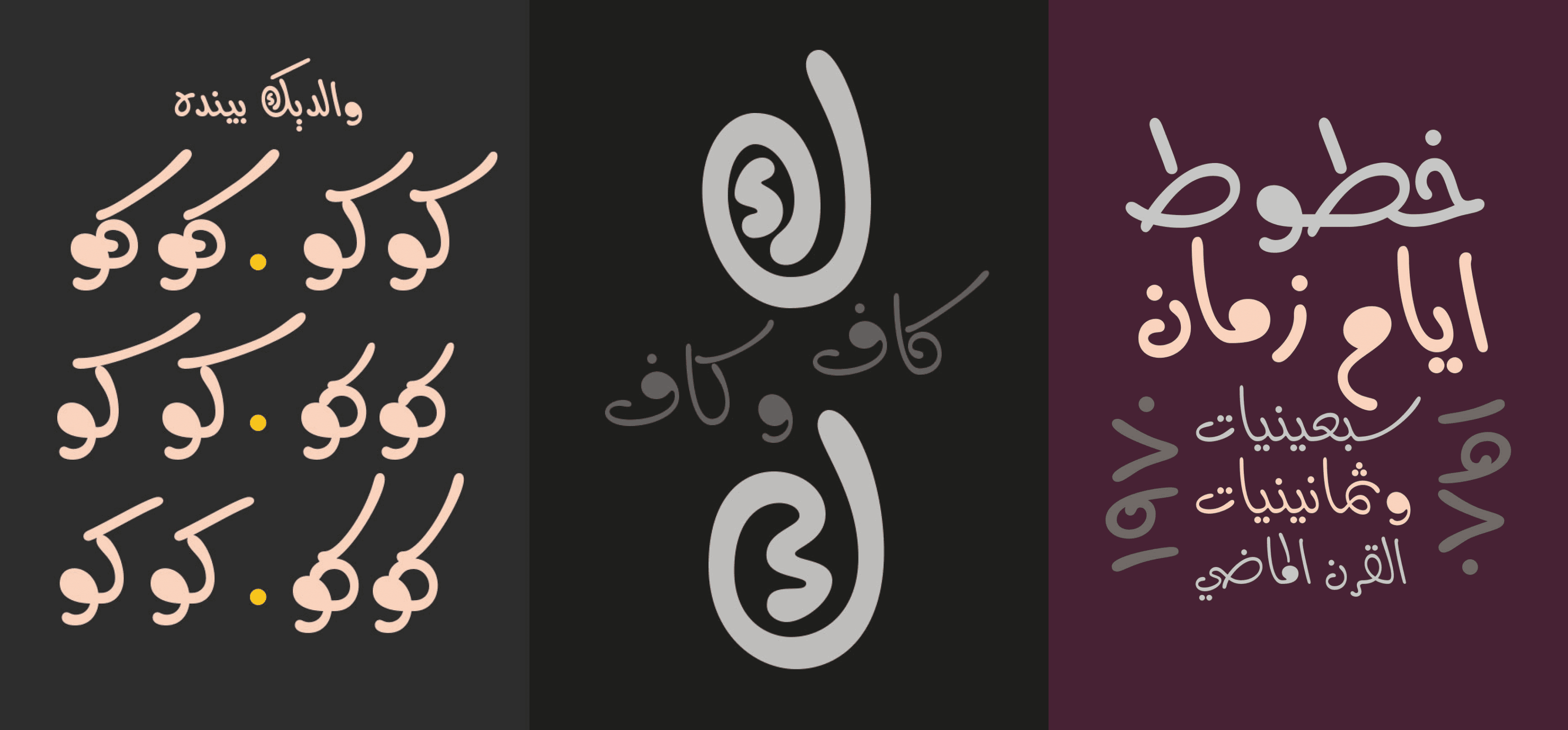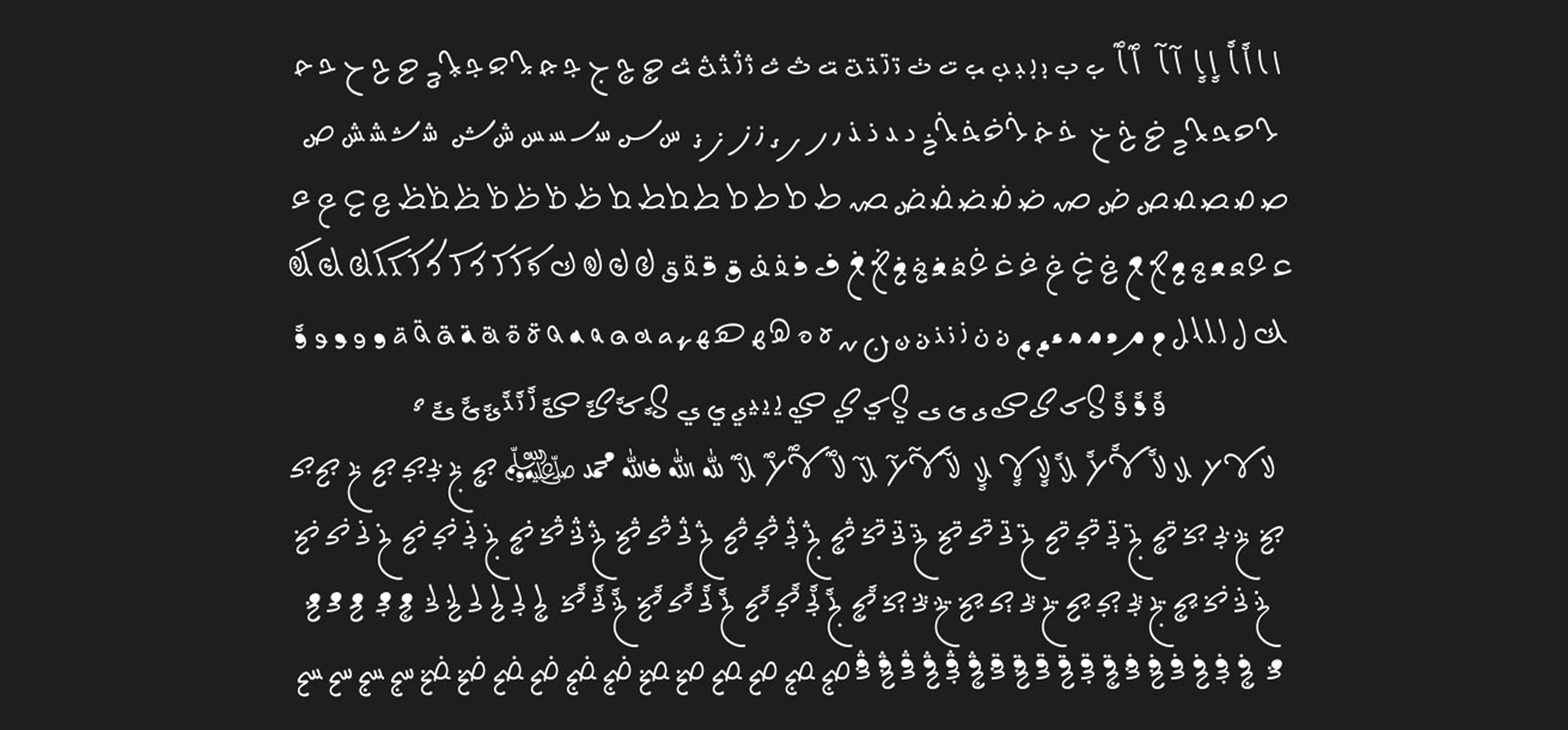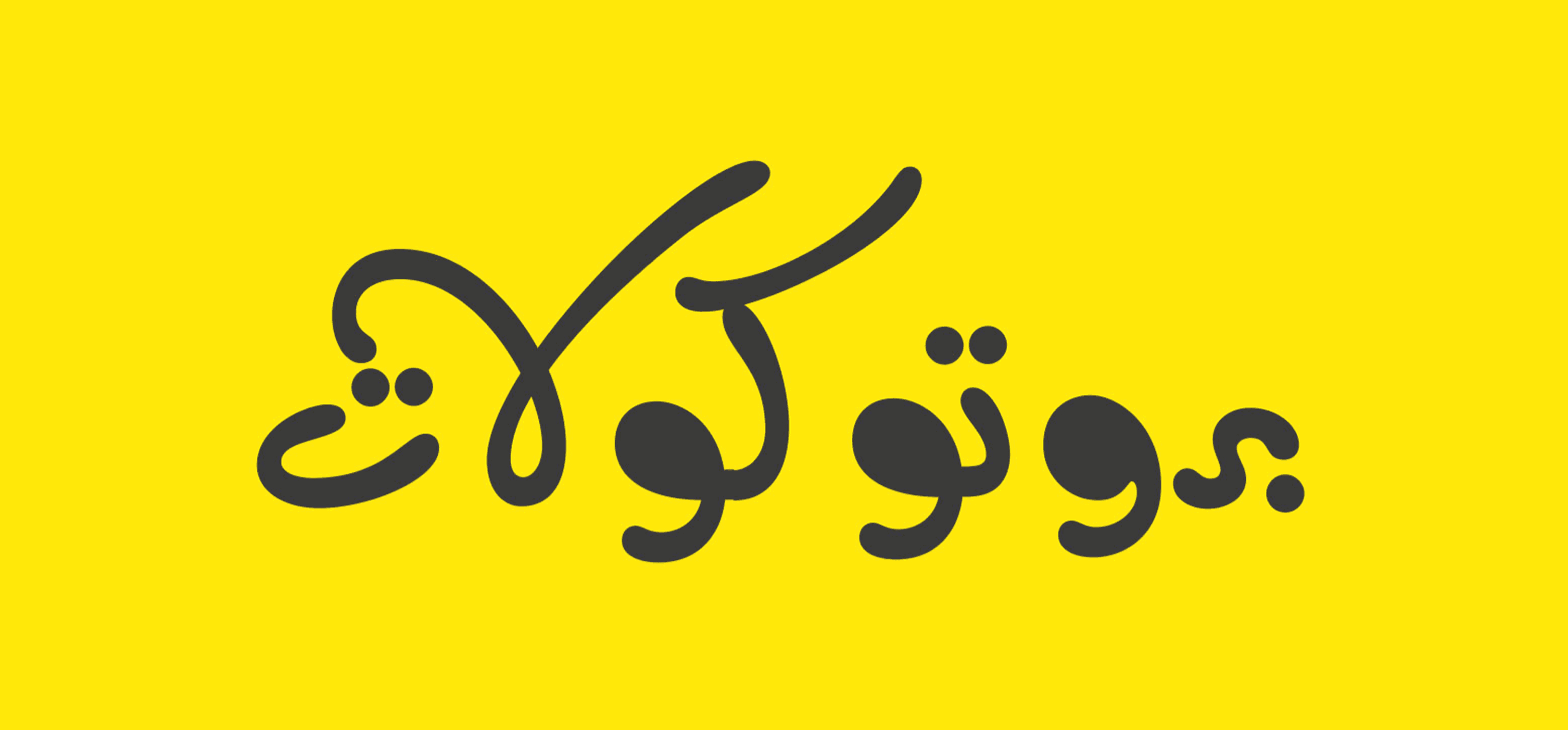
هو خط عربي معاصر يتميز بأسلوب بصري سلس ومقروء، يجمع بين الحداثة والبساطة في أشكال الحروف. يتوفر بأربعة أوزان متنوعة: خفيف جدًا (Thin)، خفيف (Light)، عادي (Regular)، وشبه عريض (SemiBold)، ما يجعله مناسبًا لمجموعة واسعة من الاستخدامات التصميمية من العناوين إلى النصوص.